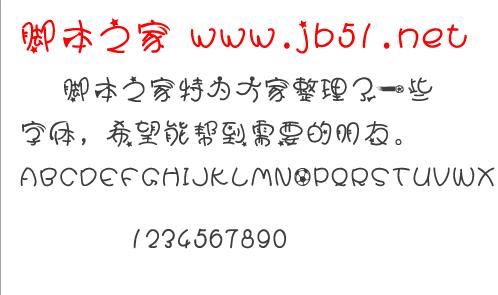
足球?qū)氊?/strong>簡(jiǎn)字體是一款百看不厭的中文字體,該字體幼圓Q萌,筆觸較為粗細(xì)適中,書(shū)寫(xiě)圓潤(rùn)可愛(ài),字里行間凡是筆畫(huà)中帶“口”字的都會(huì)換成足球黑白圖案,十分有意思,可以很好的應(yīng)用于文本裝潢、信息展示、網(wǎng)頁(yè)設(shè)計(jì)、篆刻制模、數(shù)據(jù)制作、裝潢設(shè)計(jì)、計(jì)算藝術(shù)設(shè)計(jì)、視覺(jué)設(shè)計(jì)、字帖等一切合法應(yīng)用場(chǎng)景,有喜歡的朋友可免費(fèi)下載收藏。